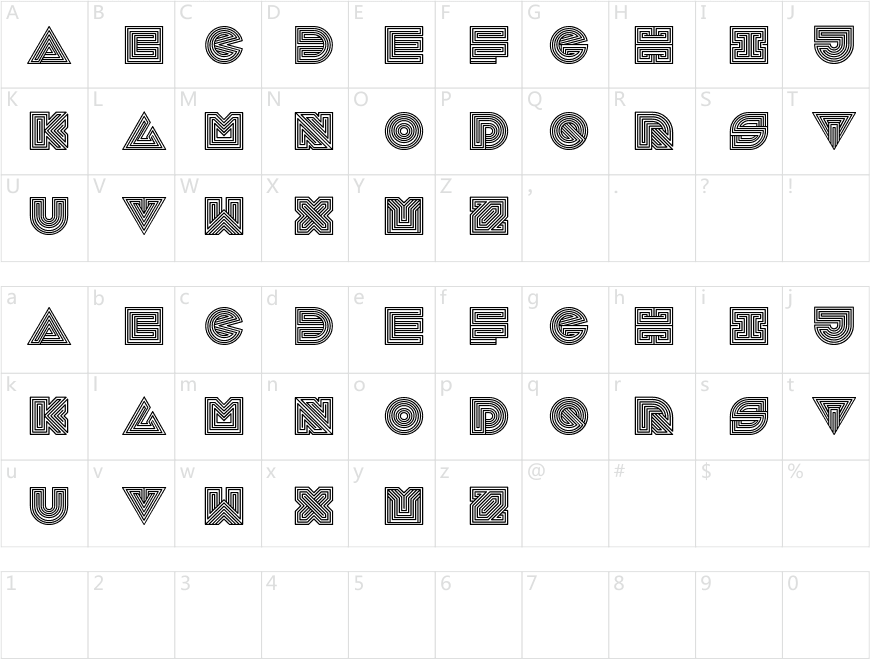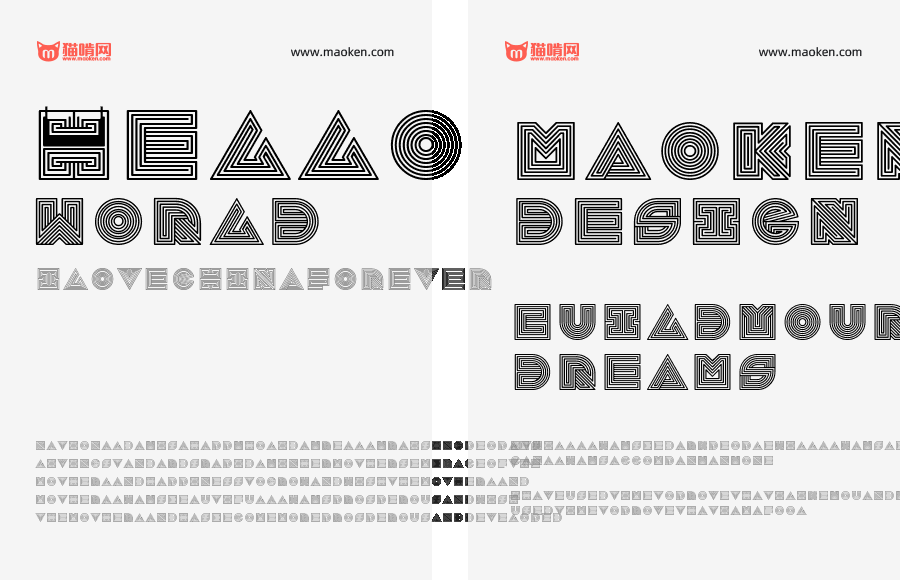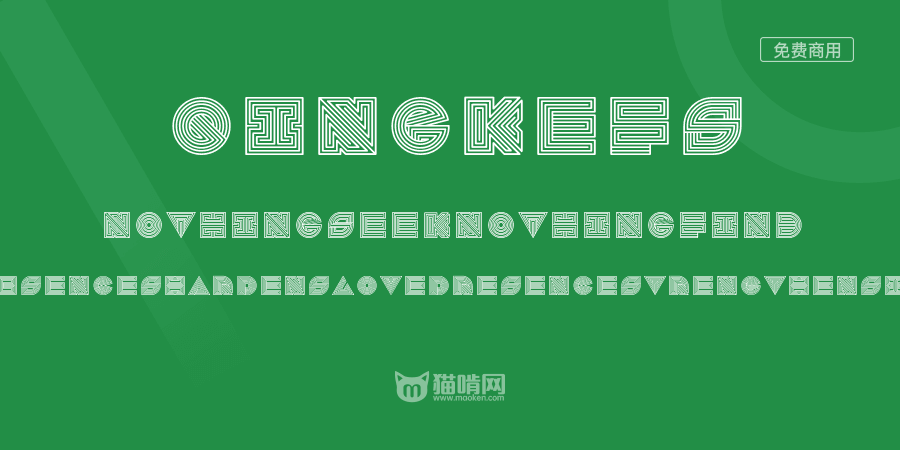
QingKeFS
字体作者:郑庆科 (中国) 字体字重:1个
PS字体名:庆科FS霓虹灯英文体字体版本:Version 1.00 更新记录
近日在整理旧文档时,发现了藏在角落里的一个字体设计文件,2012年做的一套英文字体,当时发表在站酷,近日我又整理了一下,变成了可以安装在电脑里的字体包。
由于当时只设计了26个字母,所以安装到电脑后,无论输入大写小写都只显示大写,没有标点符号数字,更没有中文。字体建议适用人群:设计师,设计爱好者,设计专业学生。